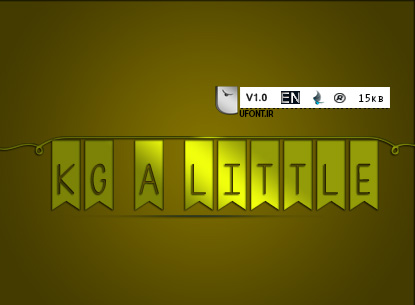
دانلود فونت جدید و زیبای لاتین با نام KGALittleSwag فونت فوق گرافیکی و زیبایی که هم اکنون شاهد آن هستید یکی از پرطرفدارترین فونت های اخیرا منتشر شده لاتین است که هم اکنون در یوفونت رایگان و پرسرعت در دسترس شماست لذت ببرید...